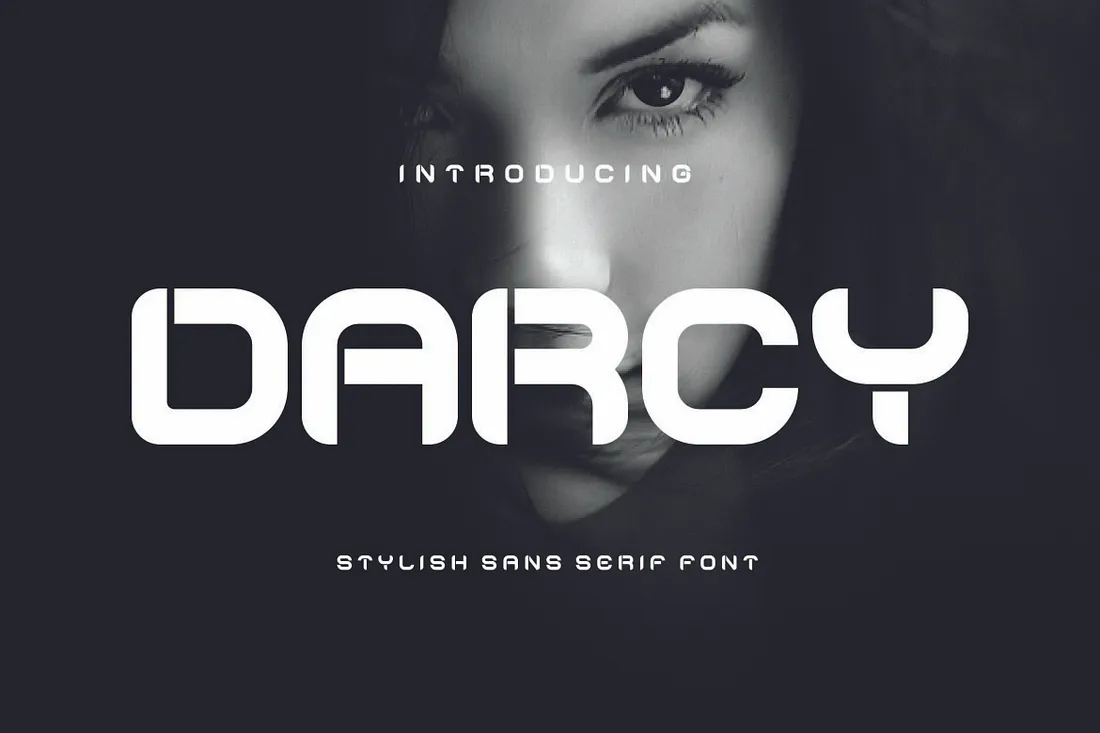
دانلود فونت Darcy Font
دارسی یک حروف sans-serif شیک و پیچیده است که برای کاربردهای مدرن طراحی شده است. دارسی با خطوط تمیز و تناسبات متعادل خود، حس ظرافت و استایل را از خود به نمایش می گذارد. این فونت همه کاره برای برندسازی، طراحی سرمقاله و تبلیغات ایده آل است، مطمئناً در هر پروژه ای بیانیه ای خواهد داشت.